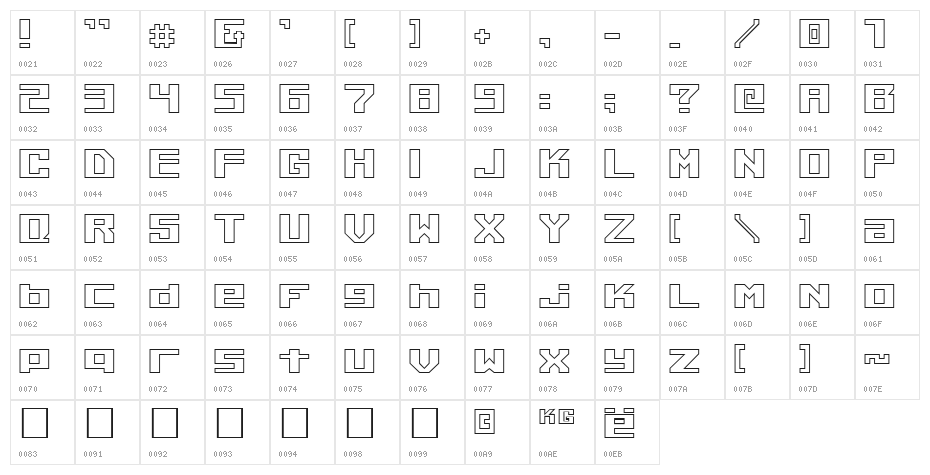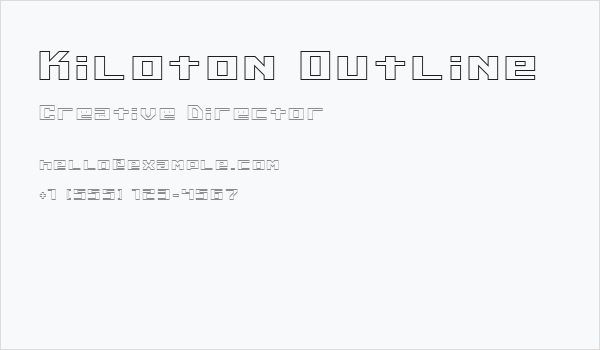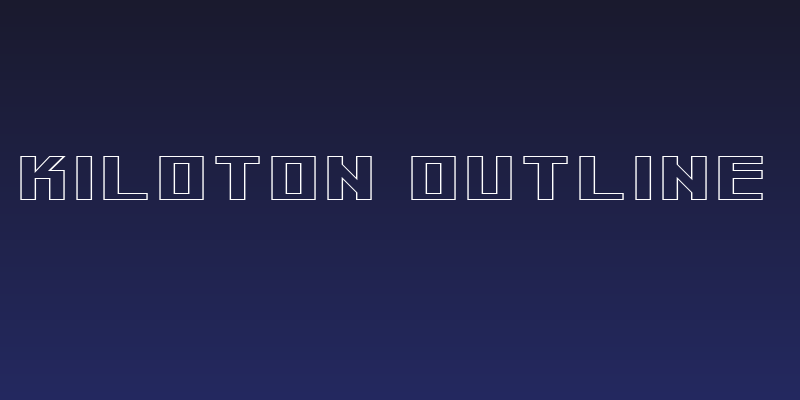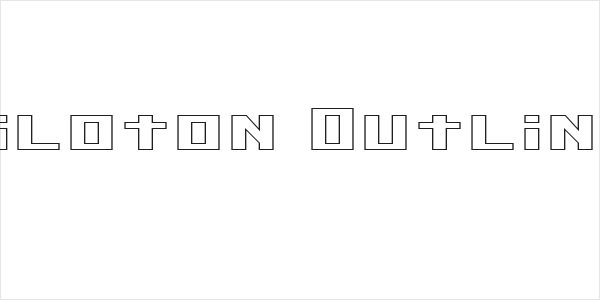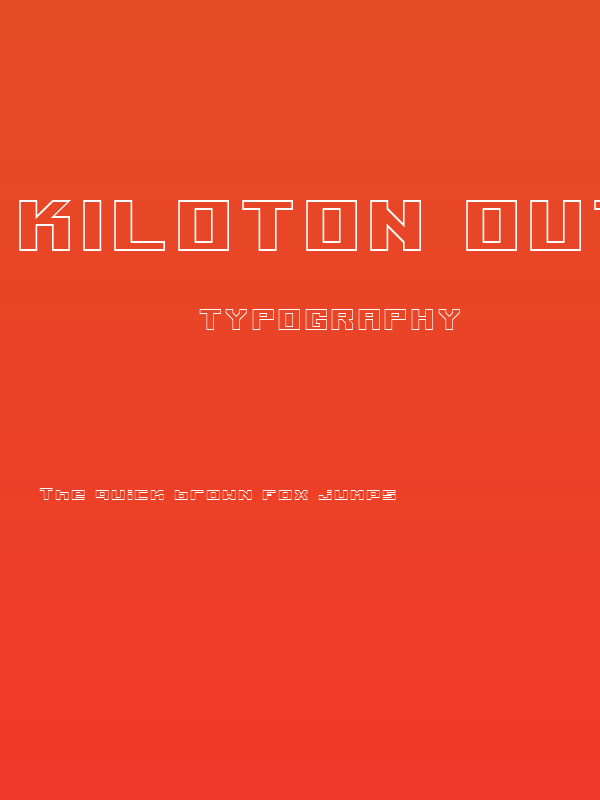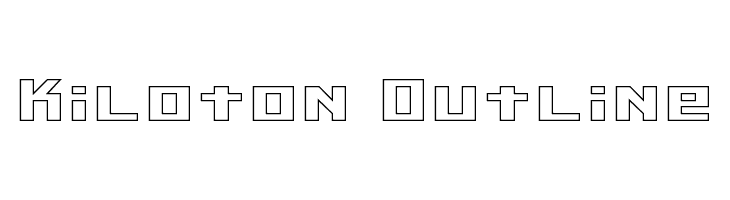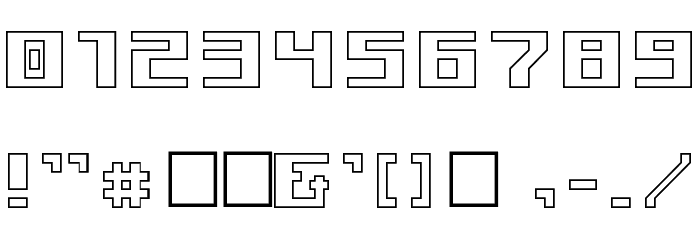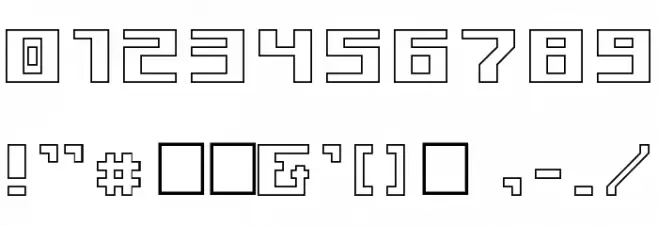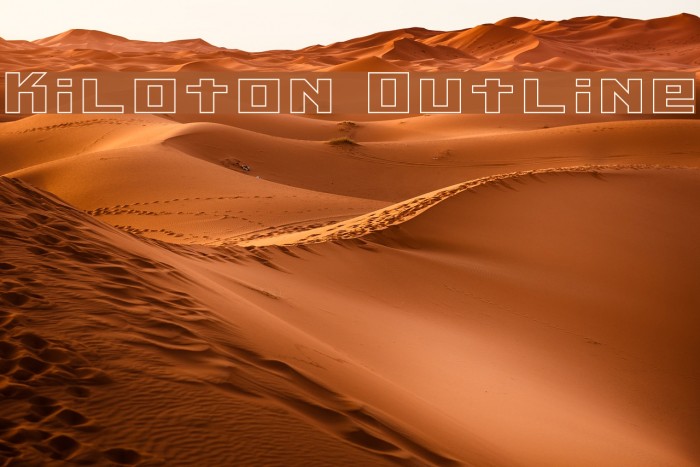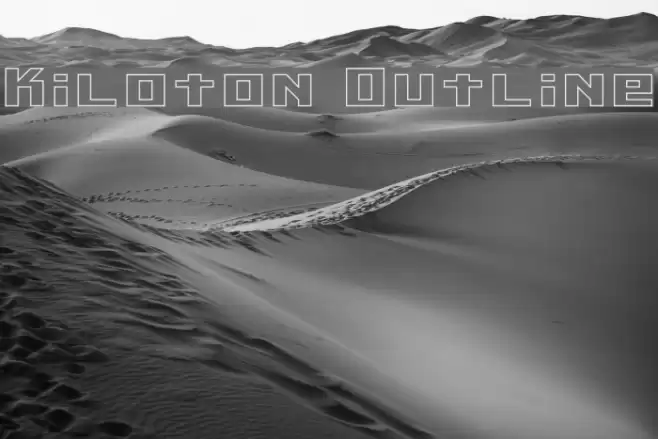
Kiloton Outline Font
| おすすめプロジェクト | Ideal for projects that require a modern and striking visual impact, such as tech branding, video game titles, posters, and digital media. |